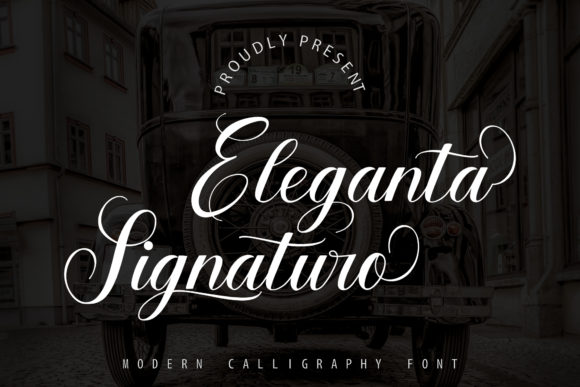
Eleganta Signaturo - это изысканный рукописный шрифт, мастерски созданный, чтобы стать настоящим фаворитом. Он сохраняет свои стильные каллиграфические влияния и в то же время чувствует себя современным и свежим. Этот шрифт закодирован в PUA, что означает, что вы с легкостью можете получить доступ ко всем глифам и следам!